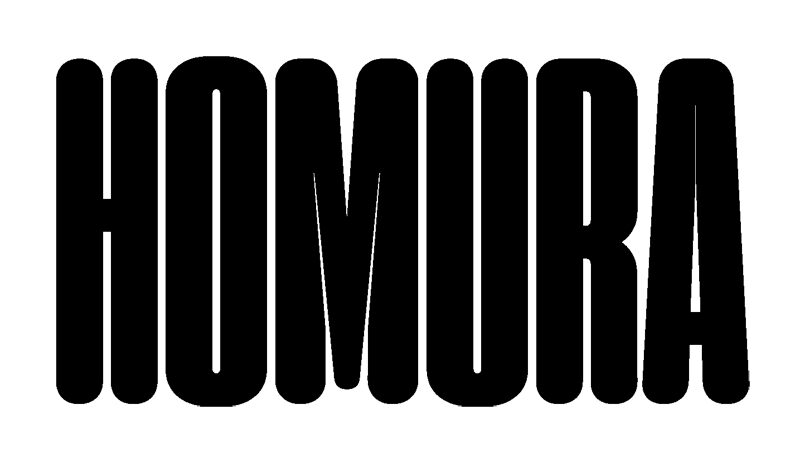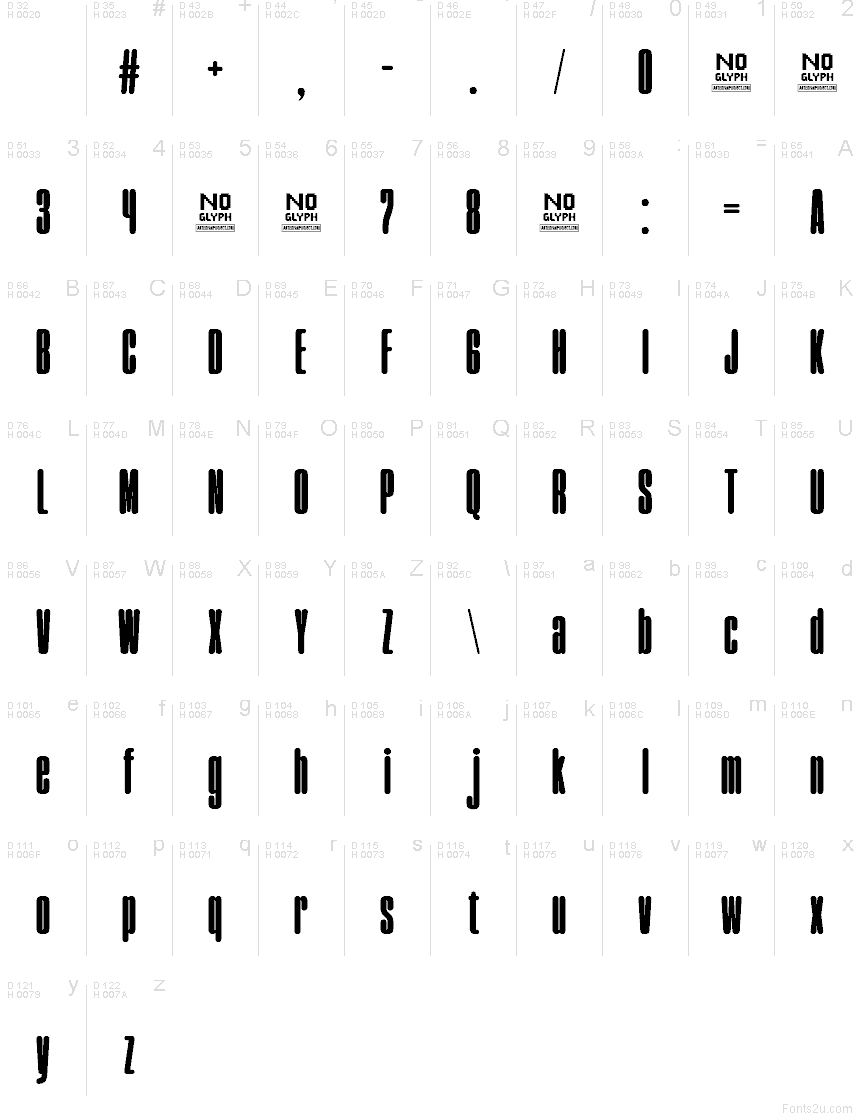
Homura Rounded di Arterfak Project è un font sans serif arrotondato, caratterizzato da una silhouette slanciata e compatta con terminali morbidi. Questa combinazione conferisce alle lettere un ritmo verticale fluido, rendendo il design grafico e d'impatto piuttosto che neutro.
Il suo ingombro ridotto lo rende perfetto per poster, copertine musicali, intestazioni di app, packaging e titoli per i social media, dove le parole brevi devono impilarsi per creare una colonna solida. La finitura arrotondata smorza la severità del tratto, rendendolo ideale per branding, etichette e titoli d'effetto che richiedono densità senza apparire meccanici o troppo rigidi.
Homura Rounded